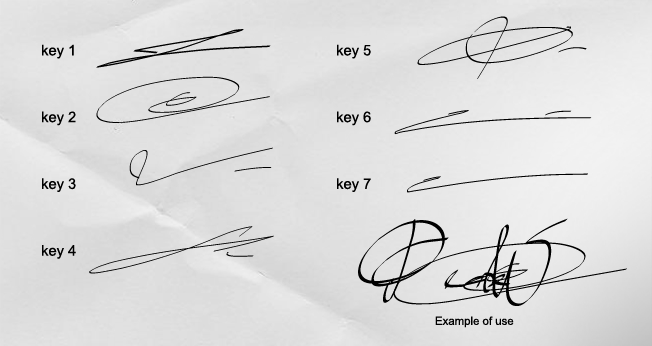
Police de caratère gratuite .ttf | Free signature font
Cette nouvelle police de caractères est un peu différente, car elle est avant tout destinée à maquetter un document signé. Je m'en sers par exemple pour maquetter un papier à en-tête pour mes clients, en créant un faux courrier en latin et une signature factice mais crédible. Les usages peuvent être multiples.
Pour l'utiliser de manière réaliste, faites comme lorsque vous signez : une majuscule, un nom, et finissez par un chiffre de 1 à 7, pour souligner votre signature !